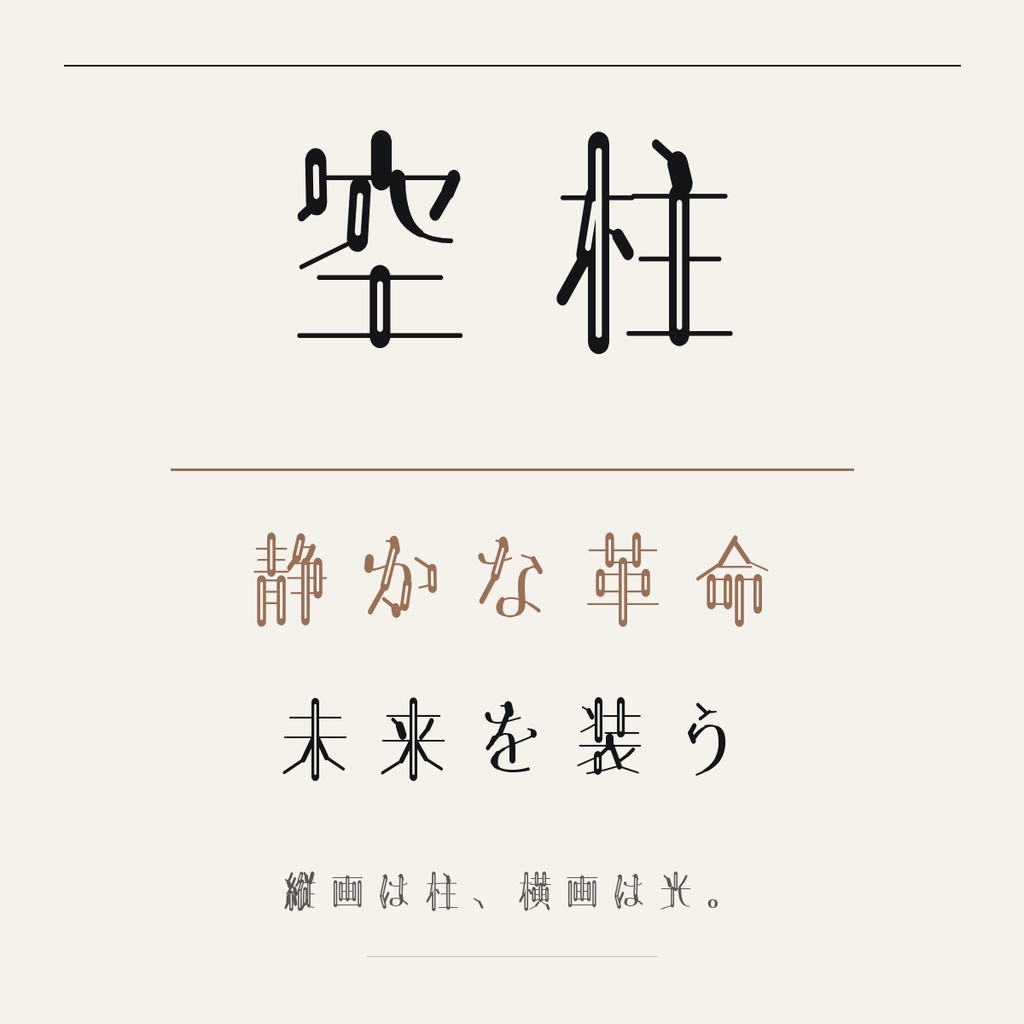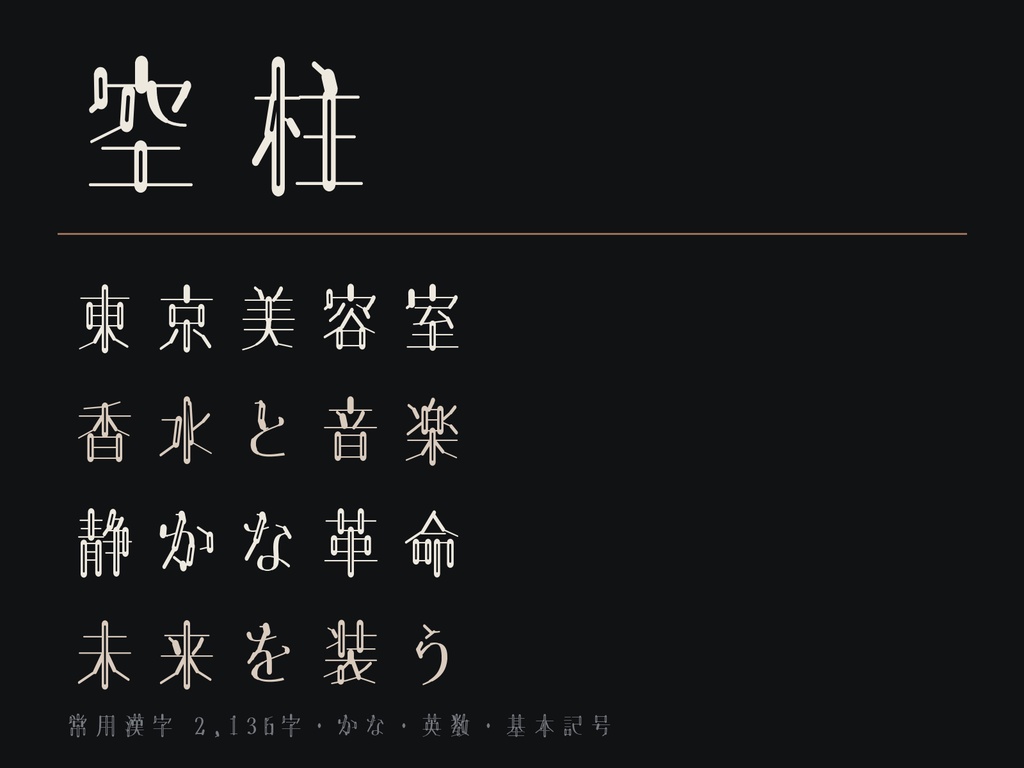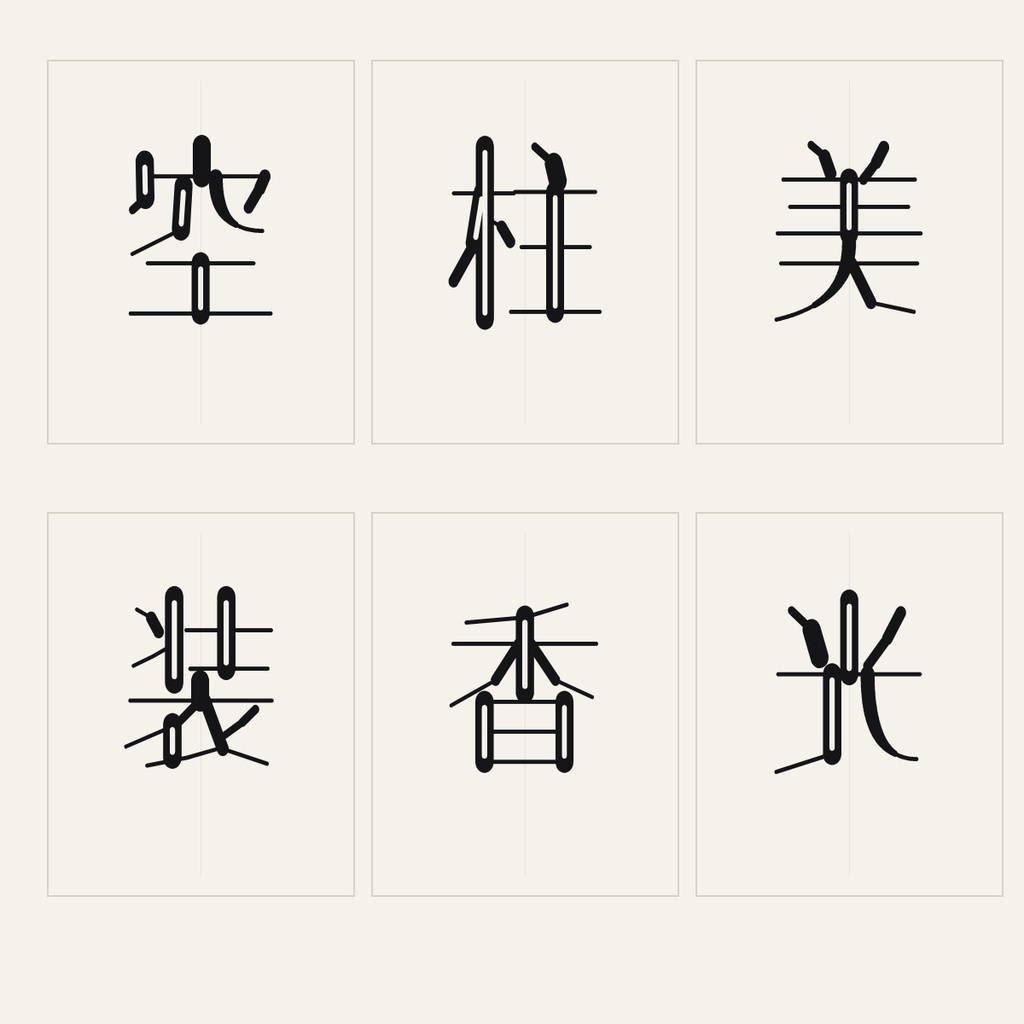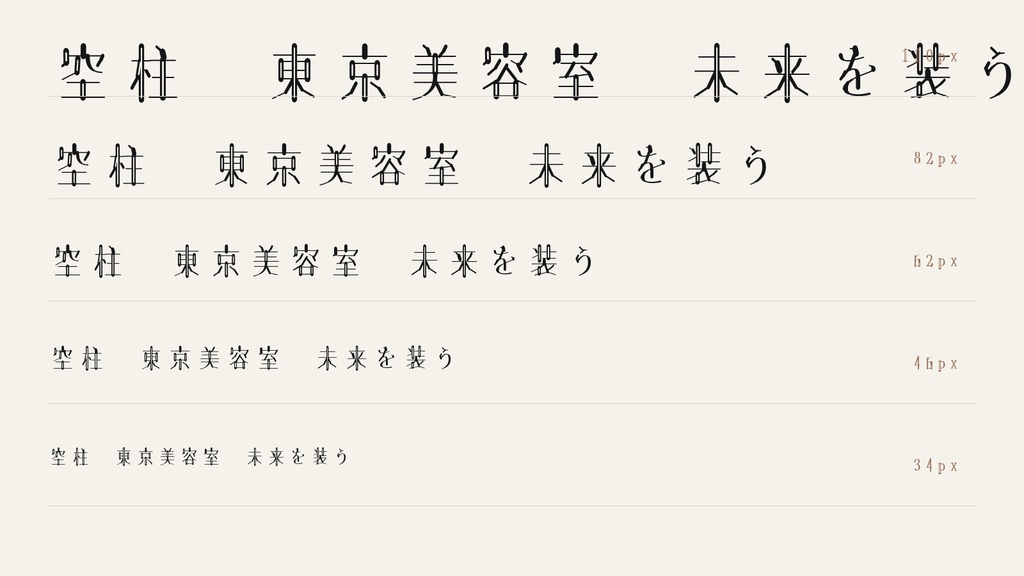
【空柱 / KUUCHU SMOOTH】上品な高コントラスト日本語フォント|常用漢字2,136字収録
【空柱(くうちゅう)Smooth】 縦画を中空の双柱、横画を細い光線として再構築した、上品で静かな緊張感を持つ日本語ディスプレイフォントです。 ファッション、化粧品、香水、ホテル、美容室、音楽作品、映画タイトル、装丁、ブランドロゴなど、余白を生かしたデザインに向いています。 ■ 価格 980円 ■ 形式 TrueType(TTF) / Windows・macOS ■ 収録 2528文字(空白を含む) 常用漢字:2136字 ひらがな・カタカナ・英数字・全角英数・基本記号 ■ 特徴 ・長い縦画だけを中空化した双柱構造 ・細い横画と滑らかな曲線による高コントラスト ・GlyphWiki KAGEデータを高密度ベジェ評価して再構築 ・見出し、ロゴ、タイトル向け ■ 利用 個人・商用利用可。ロゴ、動画、ゲーム、印刷、配信、同人・商業作品に使用できます。クレジット不要です。フォントデータの再配布・共有・転売は禁止です。詳細はZIP内の利用規約をご確認ください。 ※細線と中空部を含むため、小サイズの本文用途ではなく、28px以上の見出し用途を推奨します。